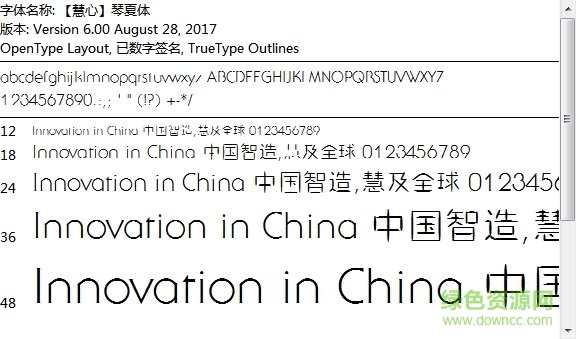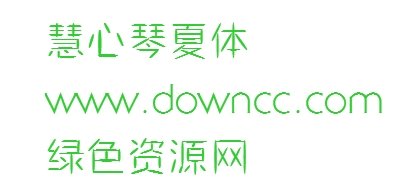
慧心琴夏體是一款書寫流暢、韻律簡潔的慧心字體,文字線條端正,整日結(jié)構(gòu)疏松,給你比較清晰舒適的視覺體驗(yàn),讓你的閱讀更加清爽,快來綠色資源網(wǎng)試試吧!
琴夏體有著極其精簡的線條和構(gòu)造,字跡纖細(xì)而娟秀,給你十分愉悅的書寫體驗(yàn),讓你的文字閱讀更加舒適,藝術(shù)設(shè)計更加簡潔大方。
慧心字體是新浪微博po主自己修改美化的字體,能更滿足手機(jī)用戶的閱讀需求,多樣的文字不僅能讓你的手機(jī)界面更加個性,還能給用戶的包裝設(shè)計、平面設(shè)計增添獨(dú)特氣質(zhì)。